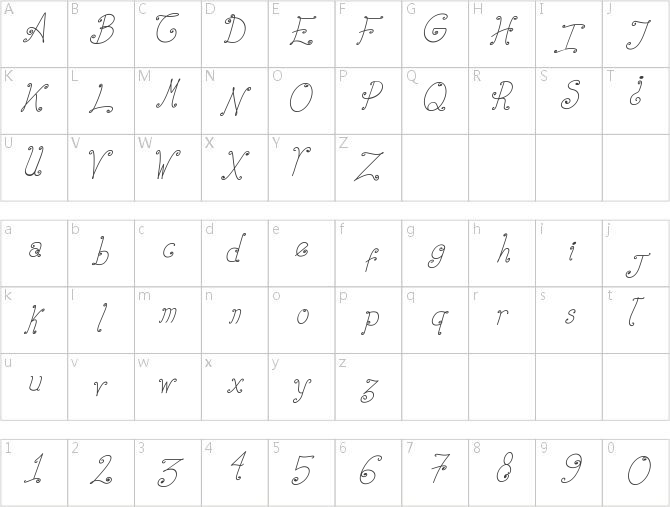
elizabeth CURSIVA
elizabeth CURSIVA介紹
elizabeth CURSIVA字體字庫是一款讓人賞心悅目、百看不厭的英文字體,適合各類廣告和產(chǎn)品包裝設計應用,字體大小0.05MB,格式為ttf字體,上傳用戶是1733150348,作者/版權(quán)方為未知